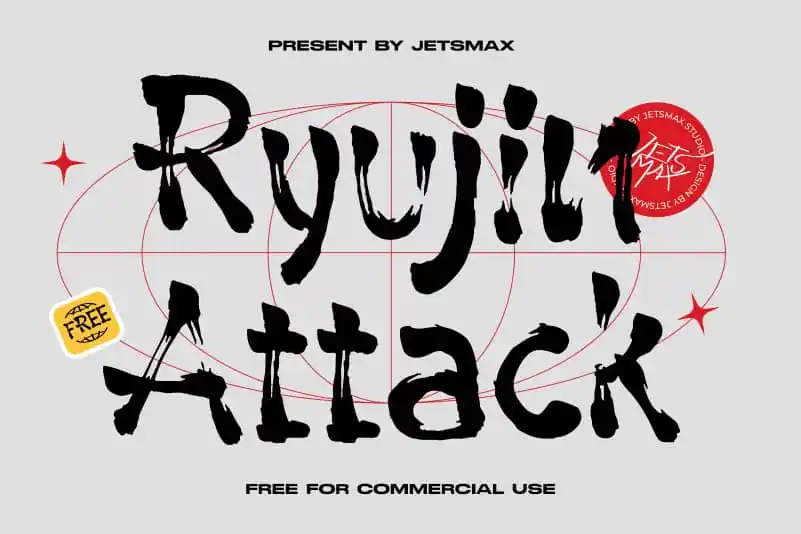
Ryujin Attack Brush Font – Download Grátis
A Ryujin Attack Brush Font é uma tipografia aquarelada que captura o espírito natural e autêntico das escritas manuscritas, oferecendo um toque de modernidade para projetos de design. Se você está procurando por uma fonte que dê um toque único e pessoal aos seus trabalhos gráficos sem precisar pagar nada, esta é a escolha certa. Com seu estilo fluido e fácil de usar, pode transformar qualquer projeto em algo único e sofisticado. Seja para criar letras chamativas em campanhas publicitárias ou adicionar um toque especial a uma assinatura profissional, esta fonte irá fazer o seu trabalho. Estranhamente perfeita para quem gosta de estilos não convencionais mas ainda precisa da simplicidade e elegância de uma boa tipografia, Ryujin Attack Brush Font é algo que todos os designers devem ter no seu arsenal. Com um design exclusivo criado pelo designer jetsmax, você pode garantir a personalização ideal para seus projetos sem comprometer o orçamento. Não importa se está trabalhando em uma campanha de marketing, criação de materiais educacionais ou qualquer outro tipo de projeto gráfico, Ryujin Attack Brush Font certamente encaixará perfeitamente e adicionará um toque diferenciado ao seu trabalho.